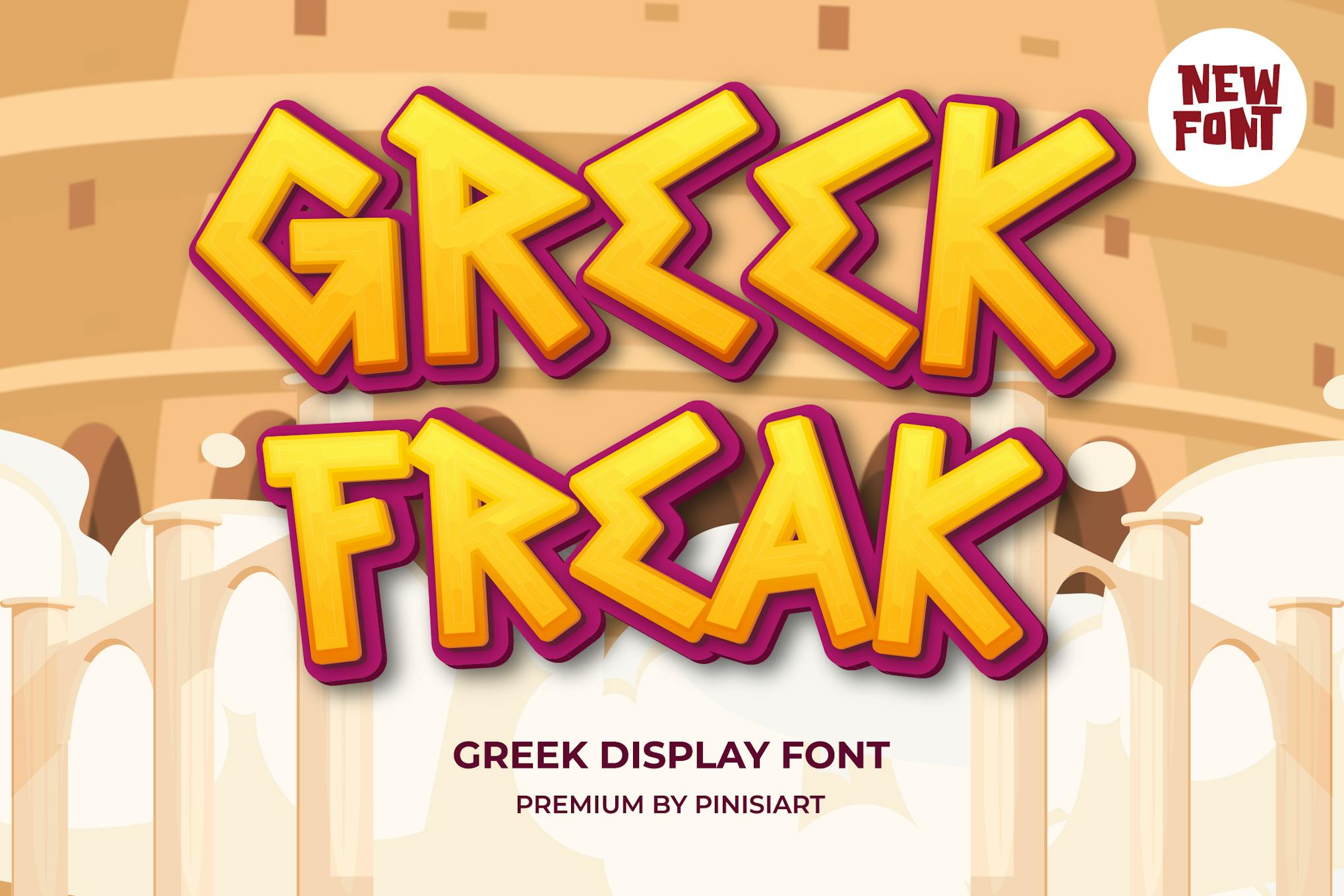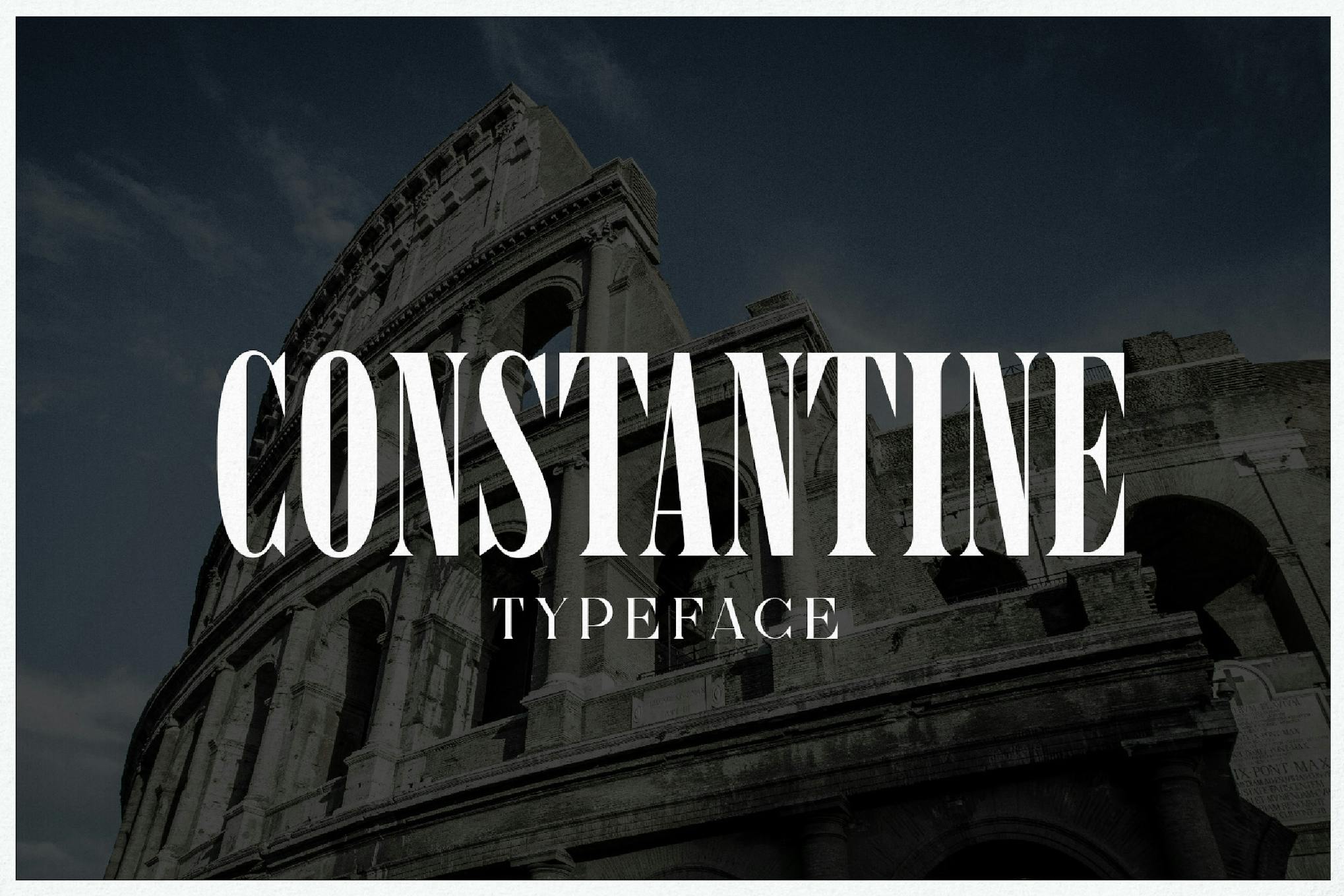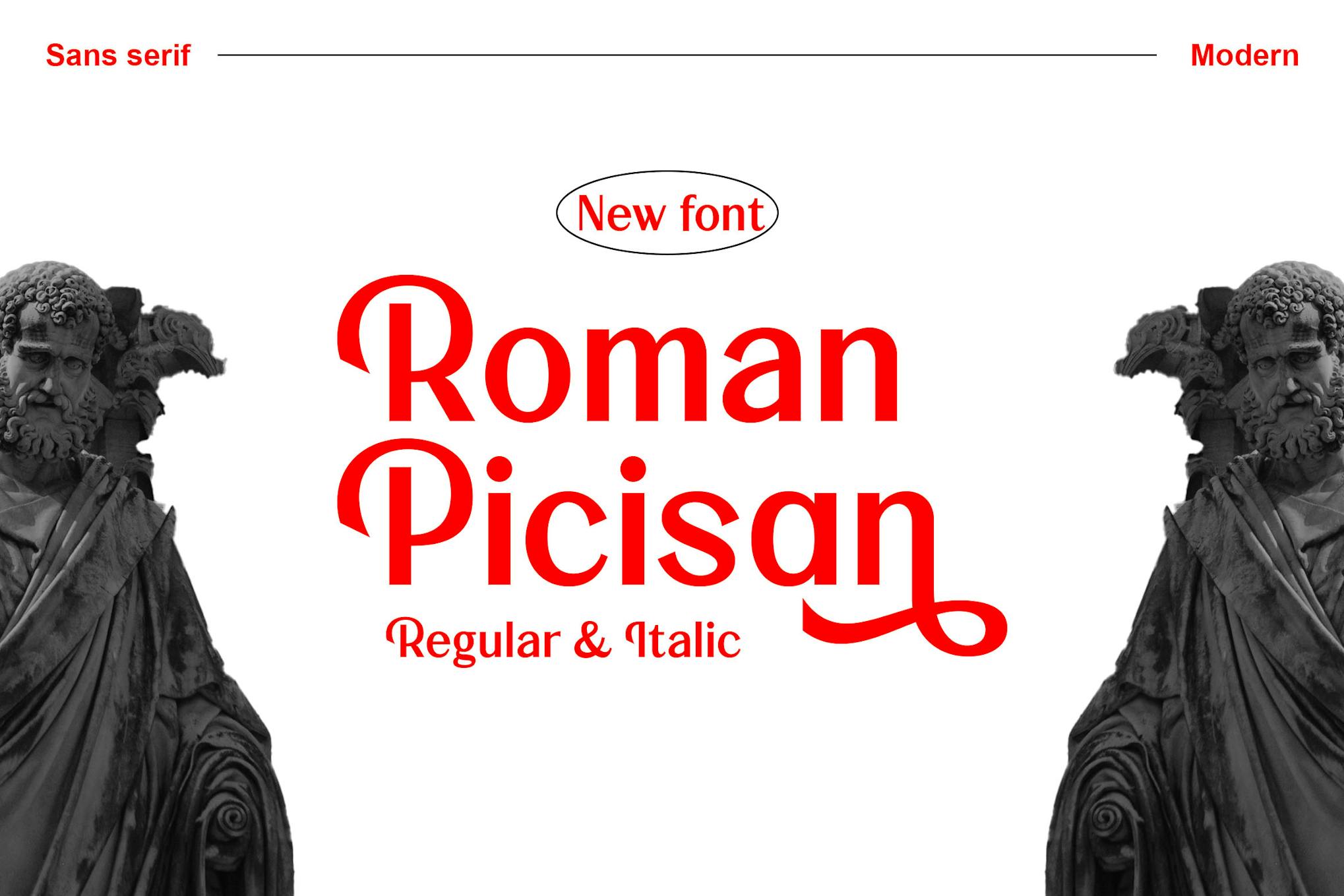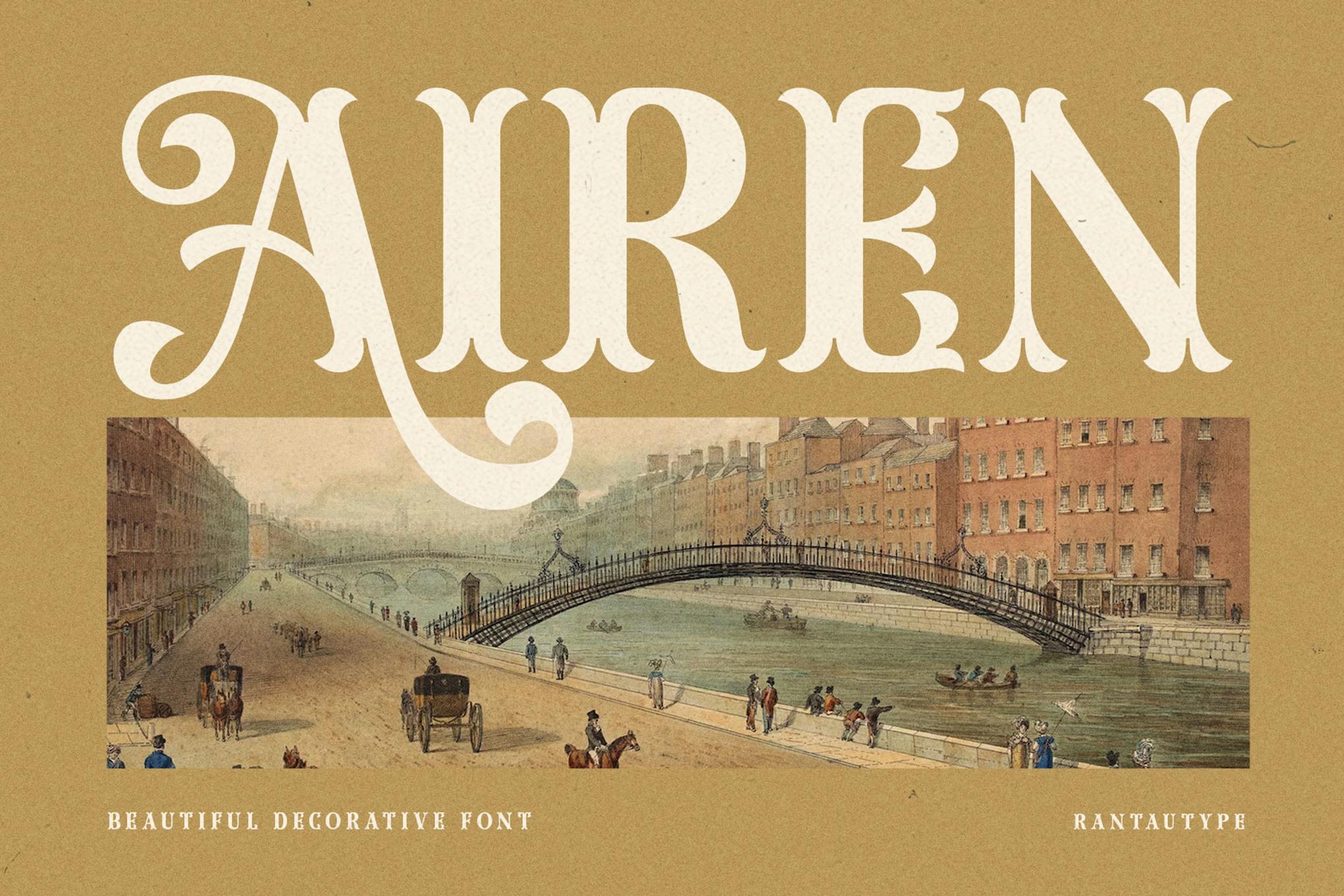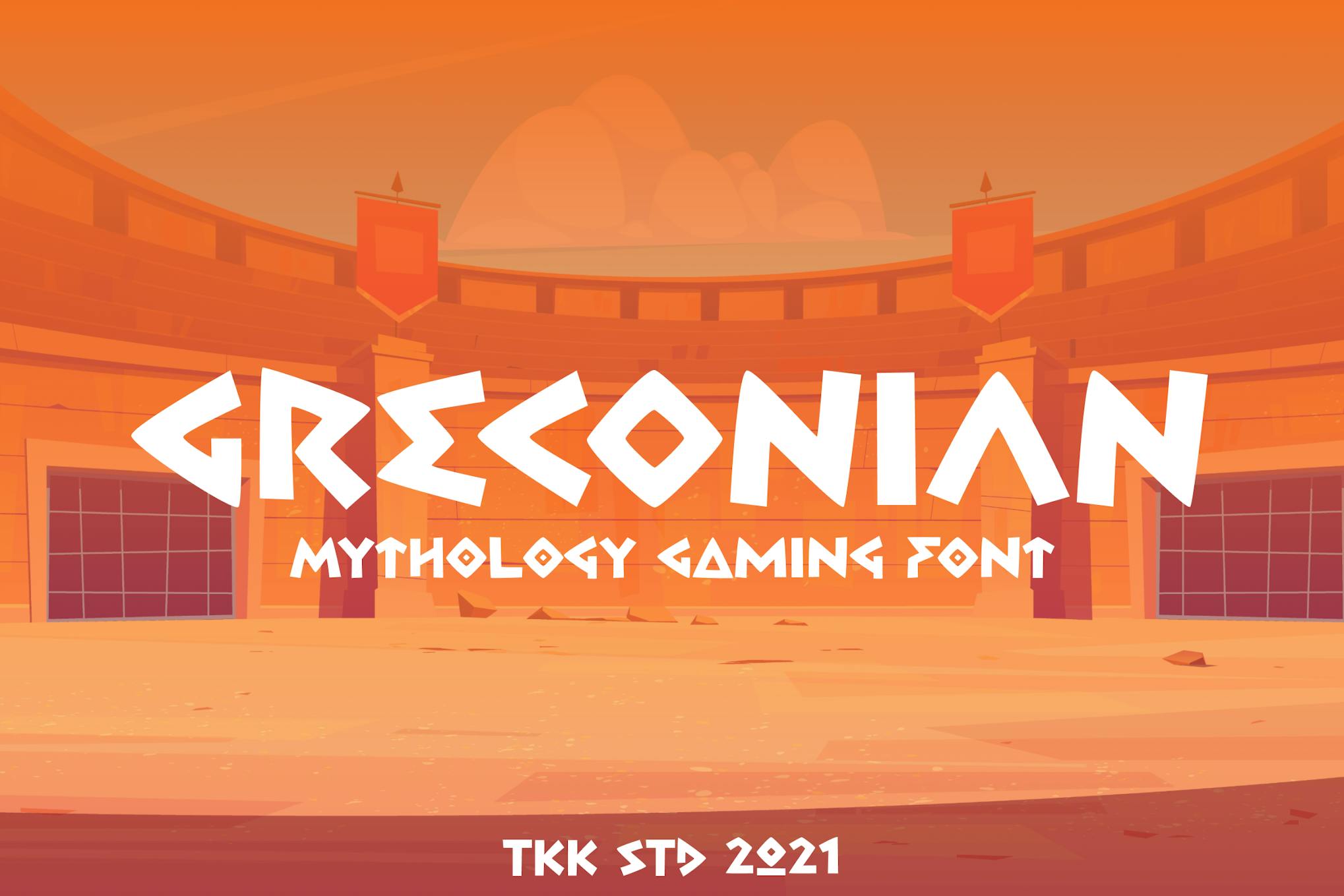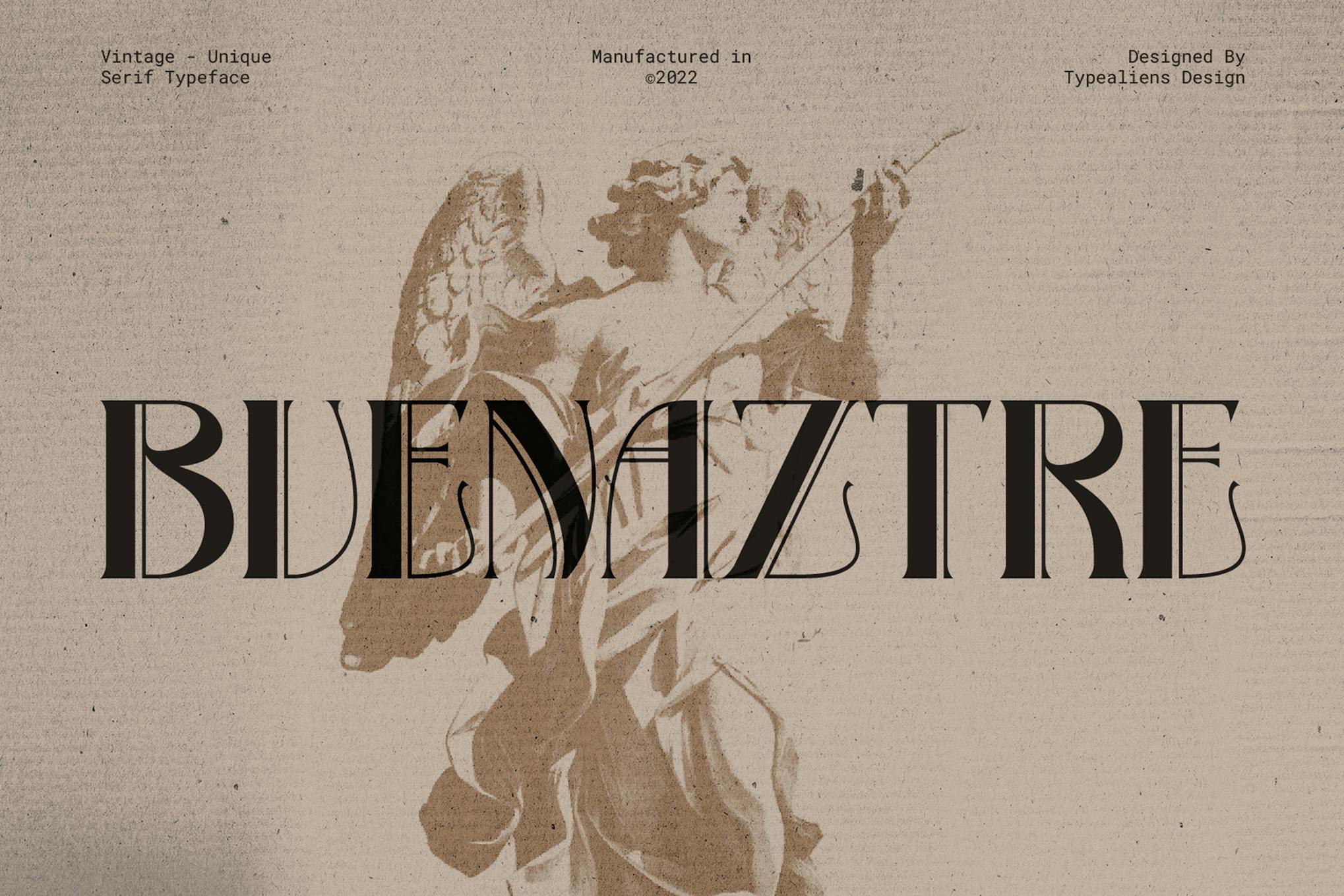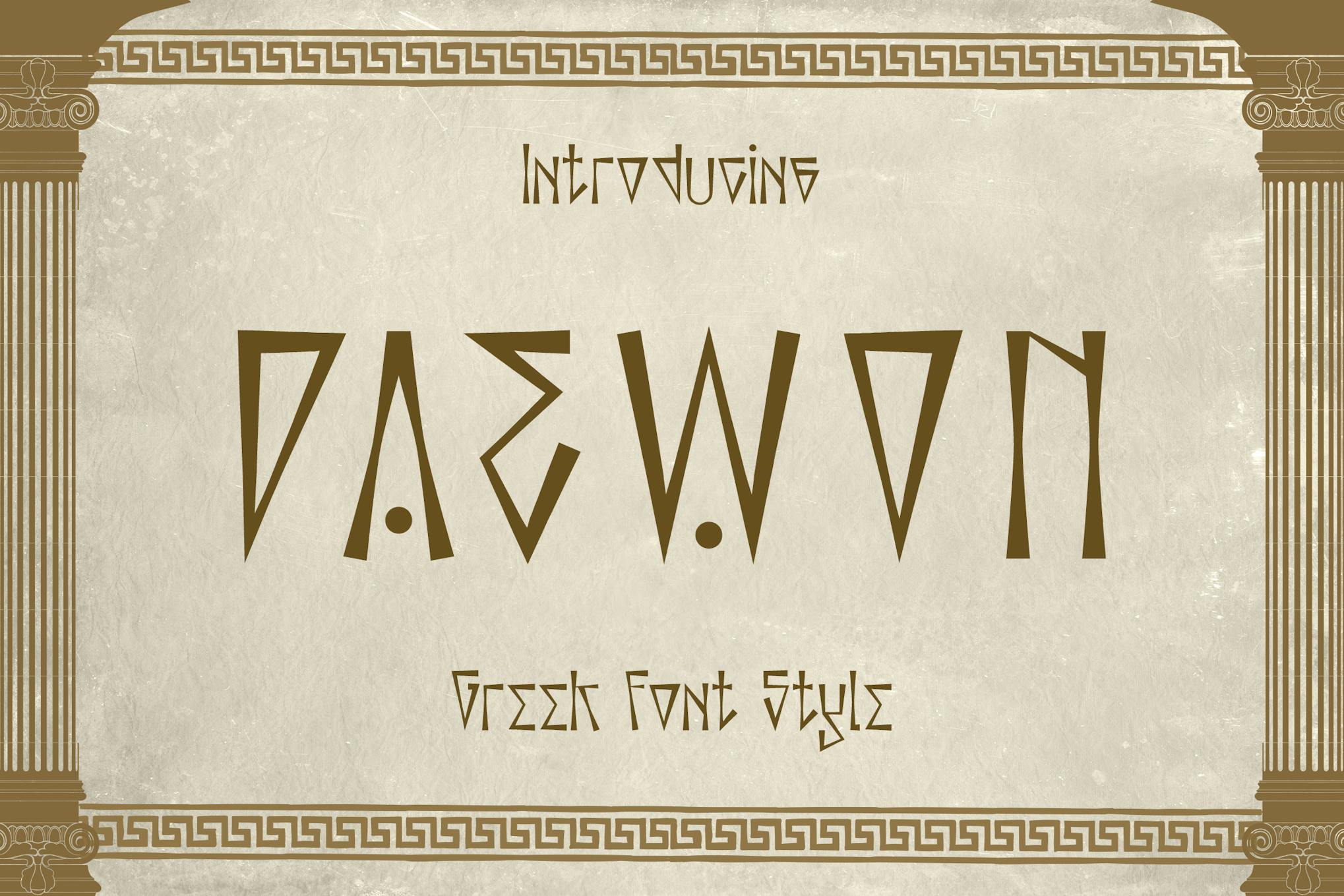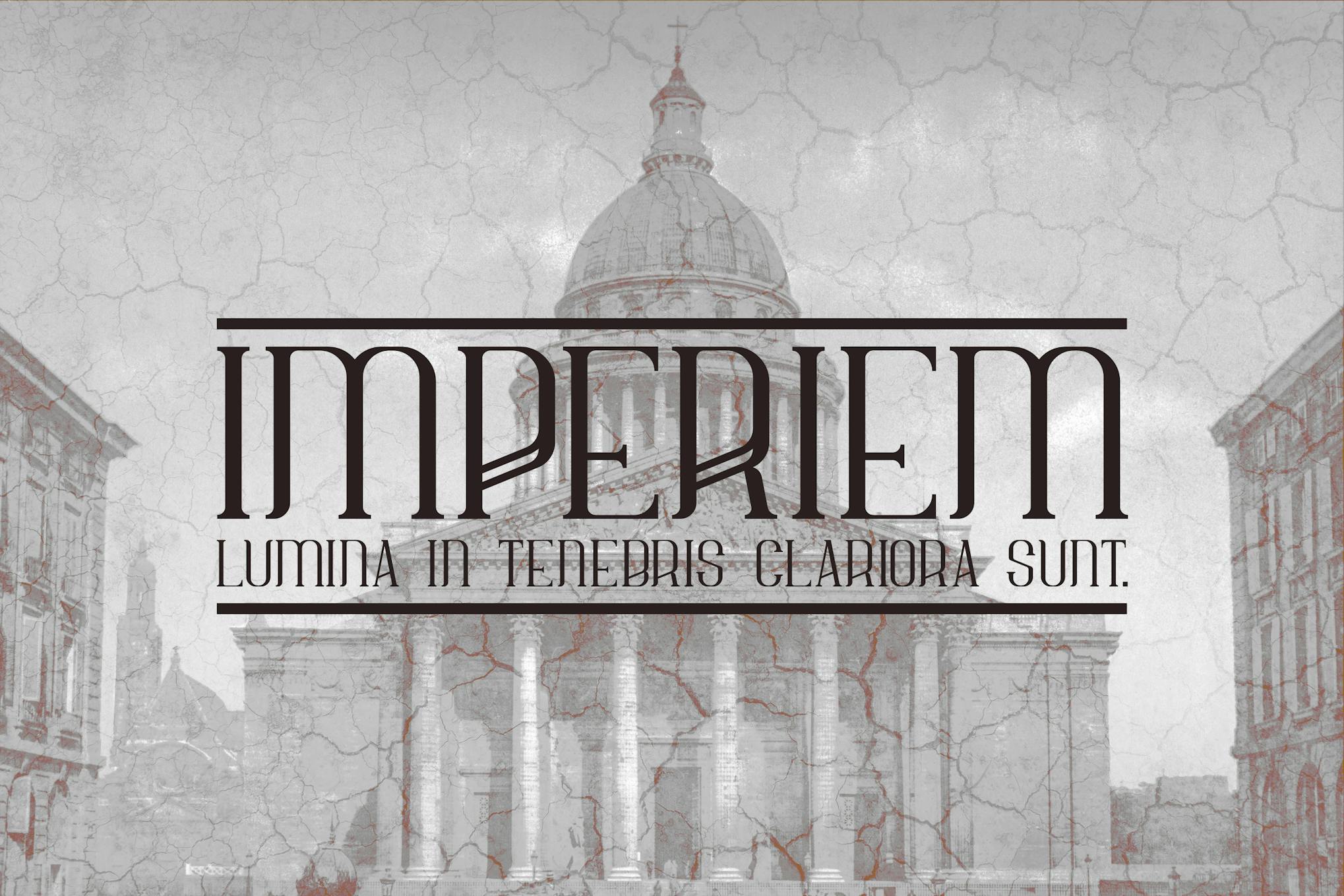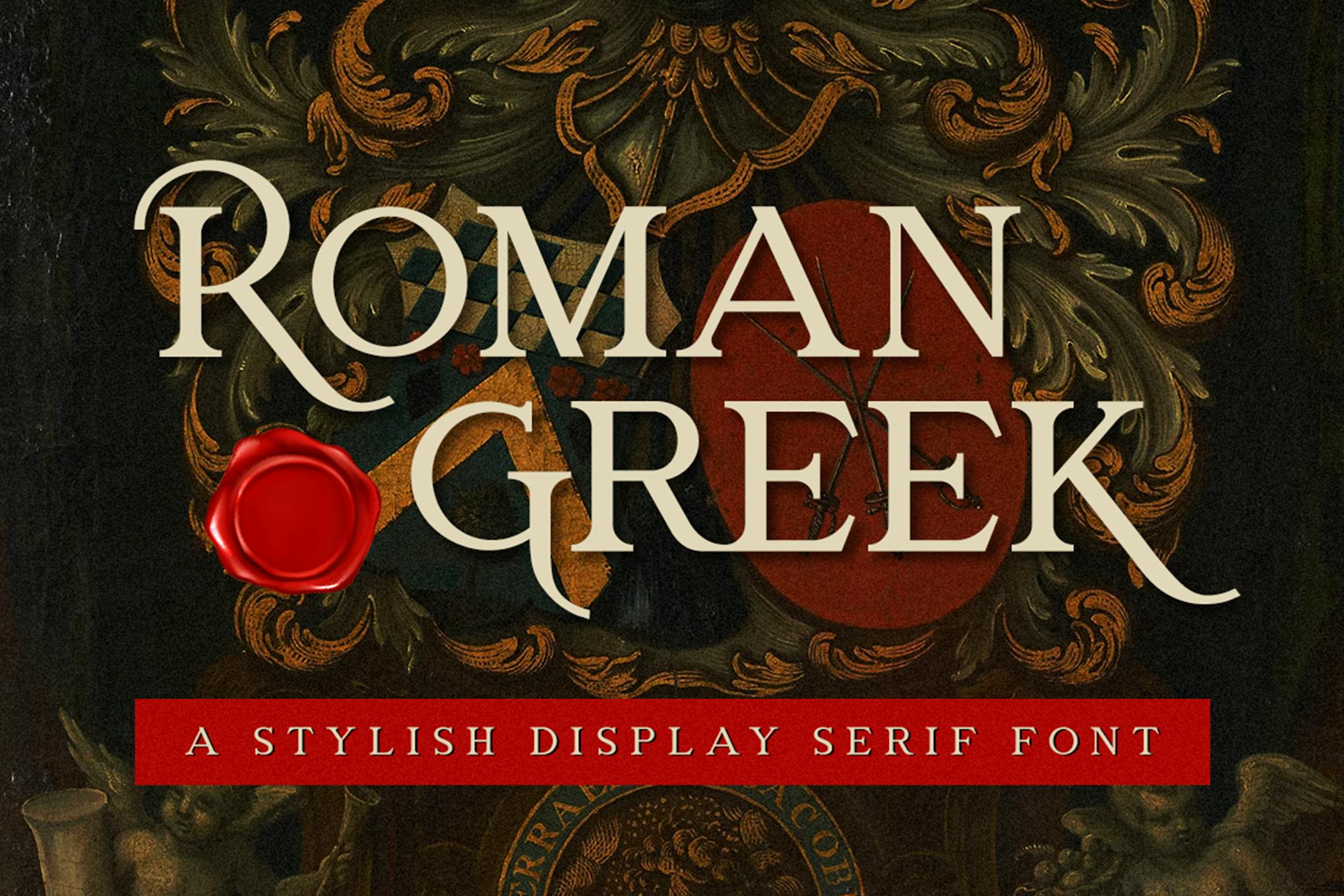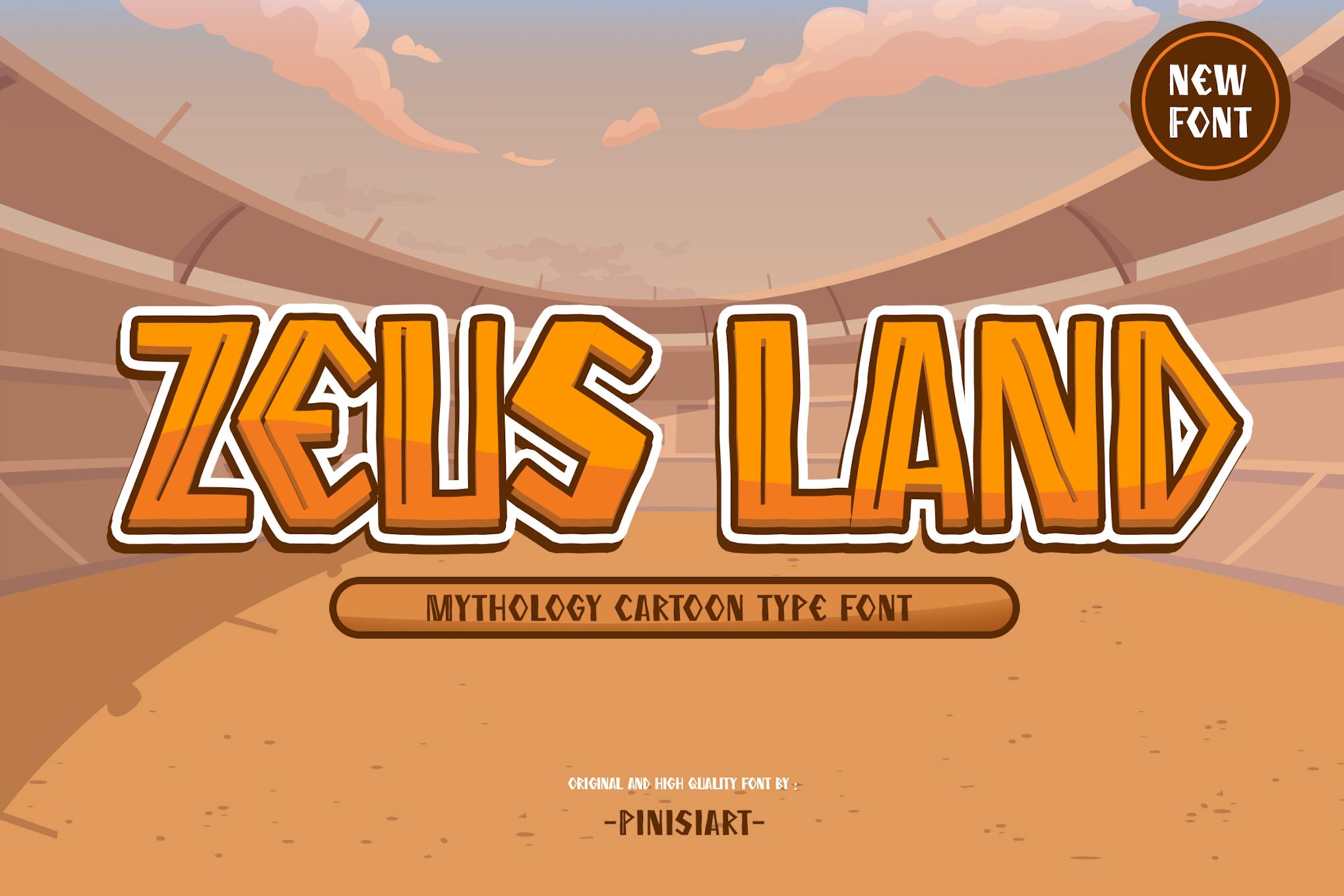
20+ Griechischer Stil Fonts (Altertum Buchstaben und Mythologie)
Ob du die Pracht des antiken Griechenlands heraufbeschwören möchtest, dein Projekt mit einem Hauch klassischer Weisheit bereichern möchtest oder einfach mit einer Schriftart hervorstechen möchtest, die eine Geschichte erzählt, griechische Schriftarten sind eine makellose Wahl.
In diesem Beitrag tauchen wir ein in die bezaubernde Welt der griechischen Schriftarten, von den traditionellen Serifen, die die gemeißelten Inschriften alter Steine nachahmen, bis hin zu modernen Anpassungen, die geometrische Präzision mit klassischem Flair verbinden, und mehr.
Unsere Sammlung umfasst sowohl Premium- als auch kostenlose Schriftarten, sodass du genau die richtige griechische Schriftart finden kannst, um dein einzigartiges Konzept zu verbessern. Diese griechischen Buchstabenschriften bieten eine großartige Möglichkeit, jedem Projekt eine unverwechselbare Note zu verleihen und eine starke visuelle Wirkung zu erzielen, die mit Sicherheit die Aufmerksamkeit des Publikums auf sich zieht.
Daewon - Greek Font Style
Diese griechische Schriftart kommt mit einem einzigartigen Buchstabendesign, das von Buchstabenformen und Metrologie des antiken Griechenlands inspiriert ist. Sie eignet sich perfekt für Poster, Buchumschläge, Einladungen oder Flyer und bietet Funktionen wie Großbuchstaben, Kleinbuchstaben, Symbole, Interpunktion, Zahlen und Ligaturen-Optionen.
Roman Greek - Display Serif Font
Roman Greek ist eine kühne Schriftart, die Eleganz und Einzigartigkeit verkörpert, inspiriert von der griechischen Mythologie und in der Lage, verschiedene Designs aufgrund ihres ordentlichen, unkomplizierten Stils zu verbessern. Sie ist vielseitig genug, um deine bevorzugte Schriftart für jedes Ereignis zu sein. Sie ist in OTF, TTF, WOFF-Formaten erhältlich und verfügt über PUA-Codierung.
Imperiem - Classic Greek Font
Imperiem verbindet architektonische Inspiration aus dem antiken Europa mit einem einzigartigen Serifenschrift-Design. Es präsentiert starke vertikale Linien, die an griechische und römische Säulen erinnern, kreativ ausgeglichen durch dünnere, verbindende Linien, die die perfekte innere Balance verkörpern. Das Paket enthält ein reguläres OTF-Format, 40 Großbuchstaben (einschließlich 14 akzentuierter Versionen) und mehr.
Bvenaztre - Vintage Greek Font
Bvenaztre ist eine vielseitige Vintage-Griechisch-Schriftart, die klassischen Art-Deco-Stil nahtlos mit geschmackvollen Serifen-Elementen verbindet. Diese Schriftart eignet sich perfekt für die Gestaltung künstlerischer Designs, die auf griechischer und römischer Ästhetik basieren. Das Paket enthält Bvenaztre in den Formaten otf, ttf, woff und woff2.
Greek Myth - Decorative Display Font
Der griechische Mythos ist eine markante und kühne Schriftart, die perfekt ist, um attraktive Titel und Überschriften zu gestalten. Sie verleiht deinem Inhalt Charakter und bietet eine Reihe von kreativen Ligaturen und Alternativen. Kompatibel mit über 100 verschiedenen Sprachen, ist es eine ausgezeichnete Wahl für die Gestaltung von Logos, Social-Media-Beiträgen, Film- oder Buchtiteln oder sogar Textdokumenten.
Commodus - All-Caps Serif Font
Commodus ist eine fesselnde Serifenschrift mit griechischem Stil, die ausschließlich in Großbuchstaben verfügbar ist. Sie bietet drei einzigartige Variationen: das „Greek“ präsentiert englische Buchstaben mit griechischer Ästhetik, während „Greek Alt“ tatsächliche griechische Zeichen verwendet, und „Regular“ ist einfach englisch.
Grave Party - Handgeschriebene griechische Schriftart
Diese verspielte griechische Schriftart ist perfekt für Halloween-Themen-Designs und lustige Poster. Die Schriftart eignet sich auch hervorragend für Social-Media-Beiträge, Website-Banner, Poster oder gedruckte Materialien. Sie umfasst Groß- und Kleinbuchstaben, Zahlen, Symbole und Interpunktion und bietet mehrsprachige Unterstützung.
Greconian - Ancient Greek Style Font
Die Schriftart Greconian fängt die Pracht und Intensität des antiken Griechenlands ein. Sie ruft Bilder von epischen Schlachten, mythologischen Göttern und mutigen Gladiatoren hervor und kombiniert dieses einzigartige Element nahtlos mit Eleganz und einem Hauch von Aggression. Ideal für eine Vielzahl von Anwendungen, von Online-Spielen und Vintage-Logos bis hin zu Postern und YouTube-Covers.
Greek Freak - Fun & Playful Font
Greek Freak ist eine verspielte, spaßige und dynamische Schriftart, inspiriert von der Pracht der griechischen Kriege und Mythologie. Sie ist die perfekte Wahl für Geschichtsbücher, Online-Spiele, Schulbriefpapier, soziale Medien und mehr. Diese Schriftart lässt antike Epen im digitalen Zeitalter mit ihrem kreativen Design lebendig werden.
Constantine - Luxury Serif Font
Constantine ist eine luxuriöse Serifenschrift, die mit der Eleganz griechischen Stils durchdrungen ist und ihre Inspiration von Konstantin dem Großen, dem römischen Kaiser, bezieht. In zwei vielseitigen Optionen präsentiert – dünn und regulär – bietet die Schrift auch 14 einzigartige Ligaturen. Mit ihrem klassischen und dennoch minimalistischen Design eignet sie sich hervorragend für eine Vielzahl von Anwendungen, einschließlich Branding, Hochzeitseinladungen, Magazinen und mehr.